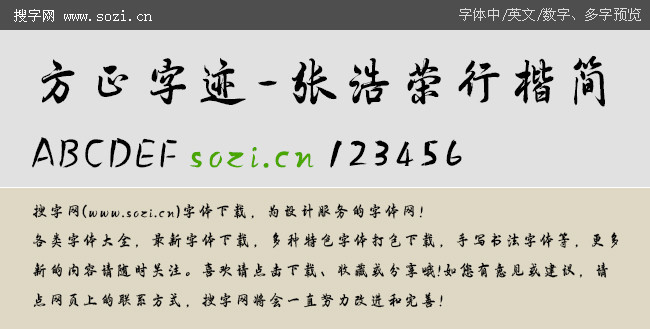
方正字跡-張浩榮行楷簡(jiǎn)
搜字網(wǎng)提供一款方正字跡-張浩榮行楷簡(jiǎn)中文字體下載,這款字體融合了行書和楷書的特點(diǎn),具有很強(qiáng)的視覺(jué)感。作者張浩榮選擇了以“二王”字體為基調(diào),采用歐陽(yáng)詢、米芾、趙孟頫眾多名家的結(jié)字,盡量表現(xiàn)出傳統(tǒng)、清新、秀氣貼近大眾的面目,同時(shí)又釋放出具有時(shí)代氣息的個(gè)性風(fēng)貌,適用于各種書刊、畫冊(cè)的設(shè)計(jì)印刷中,是報(bào)紙和雜志和書籍中常用字體, 應(yīng)用在海報(bào)、個(gè)性促進(jìn)品牌標(biāo)志設(shè)計(jì)、字體設(shè)計(jì)等環(huán)境。